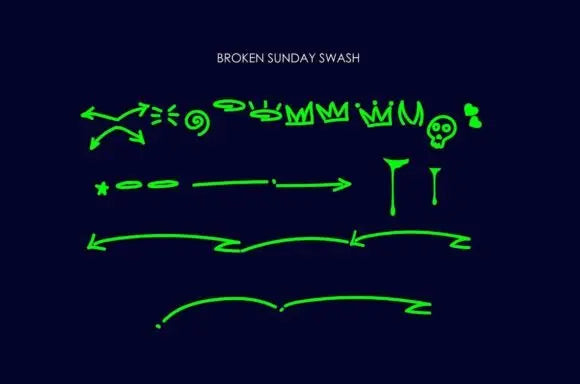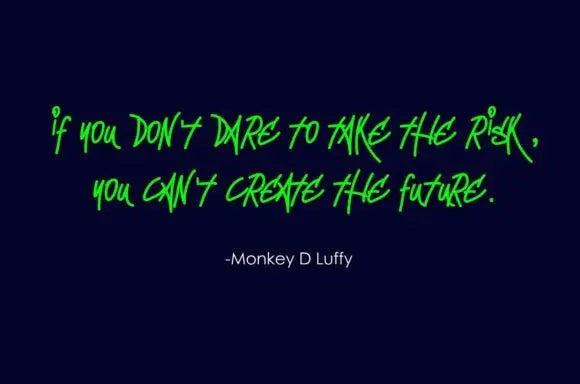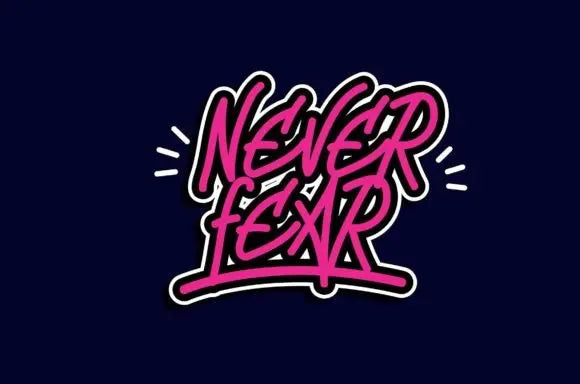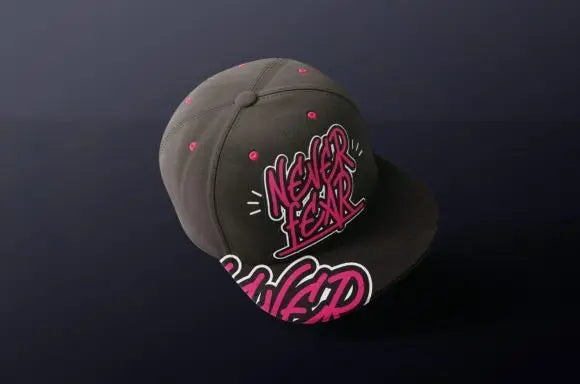
Fuente de domingo rota
Broken Sunday es una fuente de visualización con un estilo de graffiti monolínea, que presenta algunos caracteres decorativos para su increíble diseño. ¡Elevará una amplia gama de proyectos de diseño al más alto nivel, ya sea branding, encabezados, diseños, invitaciones, firmas, logotipos, etiquetas y mucho más!